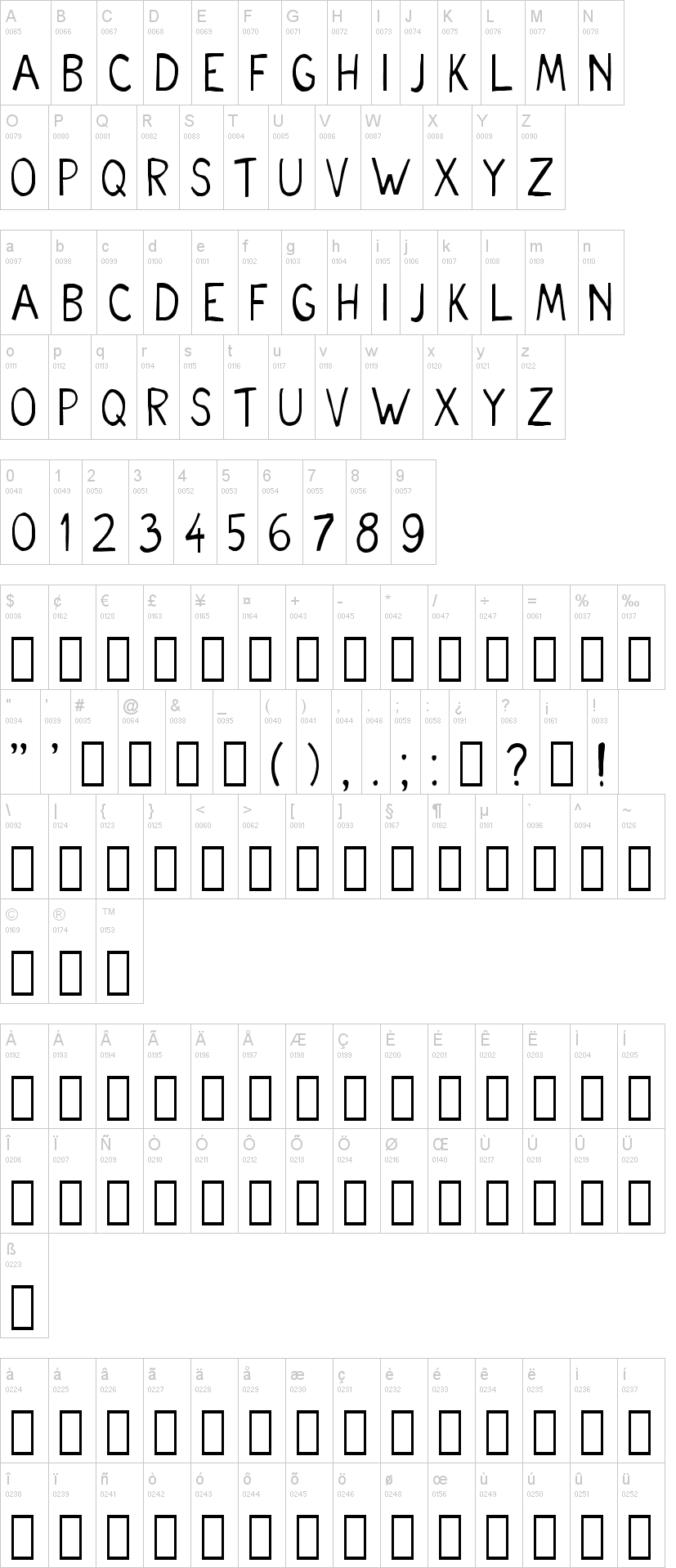
Scholar E 字体是一款英文字体,它的外观简洁,清晰,美观。字体的笔画粗细均匀,笔划清晰分明,字体的设计十分简洁,适合用于文字排版,也可以用于图片的排版。它的字形设计灵活,可以容易地实现英文文字的排版效果,而且还可以改变文字的大小,以便更好地表达文字的意思。内容介绍
Scholar E是一款非常不错的手写艺术字体,具有很好的视觉感,适合于文化类的宣传设计、商业类品牌的广告和产品包装设计以及个性化文字排版等较多场景。